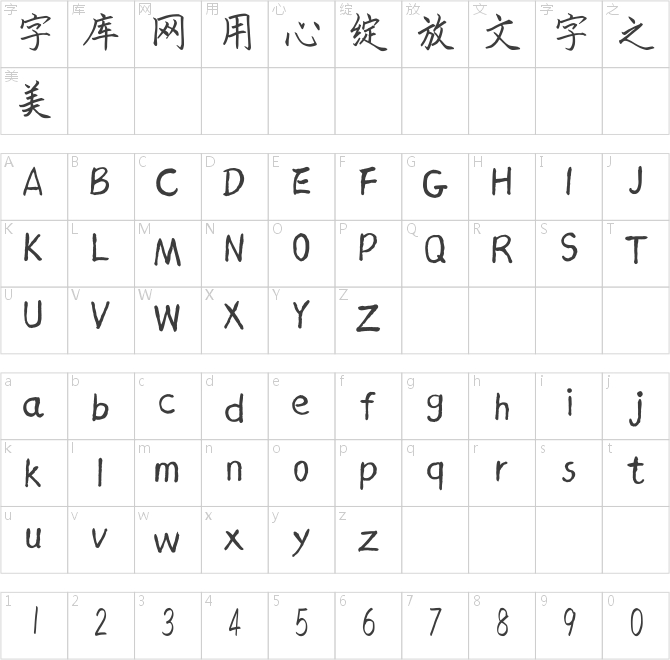
漢標(biāo)精工閨蜜楷
楷體
漢標(biāo)精工閨蜜楷體字體字庫(kù)是一款讓人賞心悅目、百看不厭的中文字體,適合各類(lèi)廣告和產(chǎn)品包裝設(shè)計(jì)應(yīng)用,字體大小9.23MB,格式為ttf字體,上傳用戶(hù)是漢標(biāo)文創(chuàng),作者/版權(quán)方為漢標(biāo)字庫(kù)